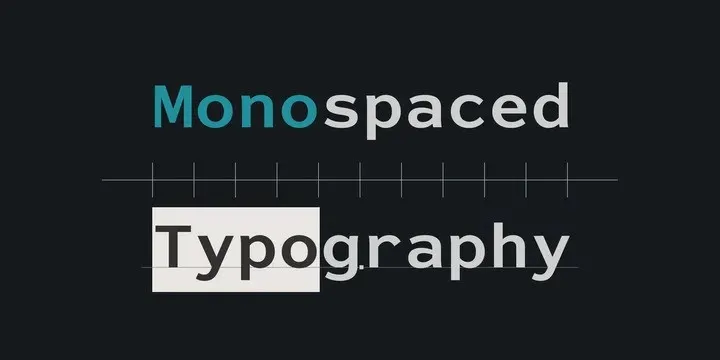
Best Choice Font – Download Grátis
A Best Choice Font é uma elegante tipografia de sans-serif criada por Dharma Type, inspirada em projetos de marca baseados na originalidade suíça. Esta fonte minimalista apresenta um design excepcionalmente refinado e uma vasta gama de recursos para uso fácil e eficiente. Ela se destaca não apenas pela sua aparência simples e limpa, mas também por suas características únicas que a tornam ideal para projetos digitais modernos e criativos. Seja você um designer experiente ou iniciante, a Best Choice Font será uma escolha ótima para estilizar qualquer tipo de conteúdo em seu site ou aplicativo. Com a sua facilidade de uso e beleza minimalista, é claro que esta fonte vai se tornar parte do seu arsenal de ferramentas indispensáveis no processo criativo.